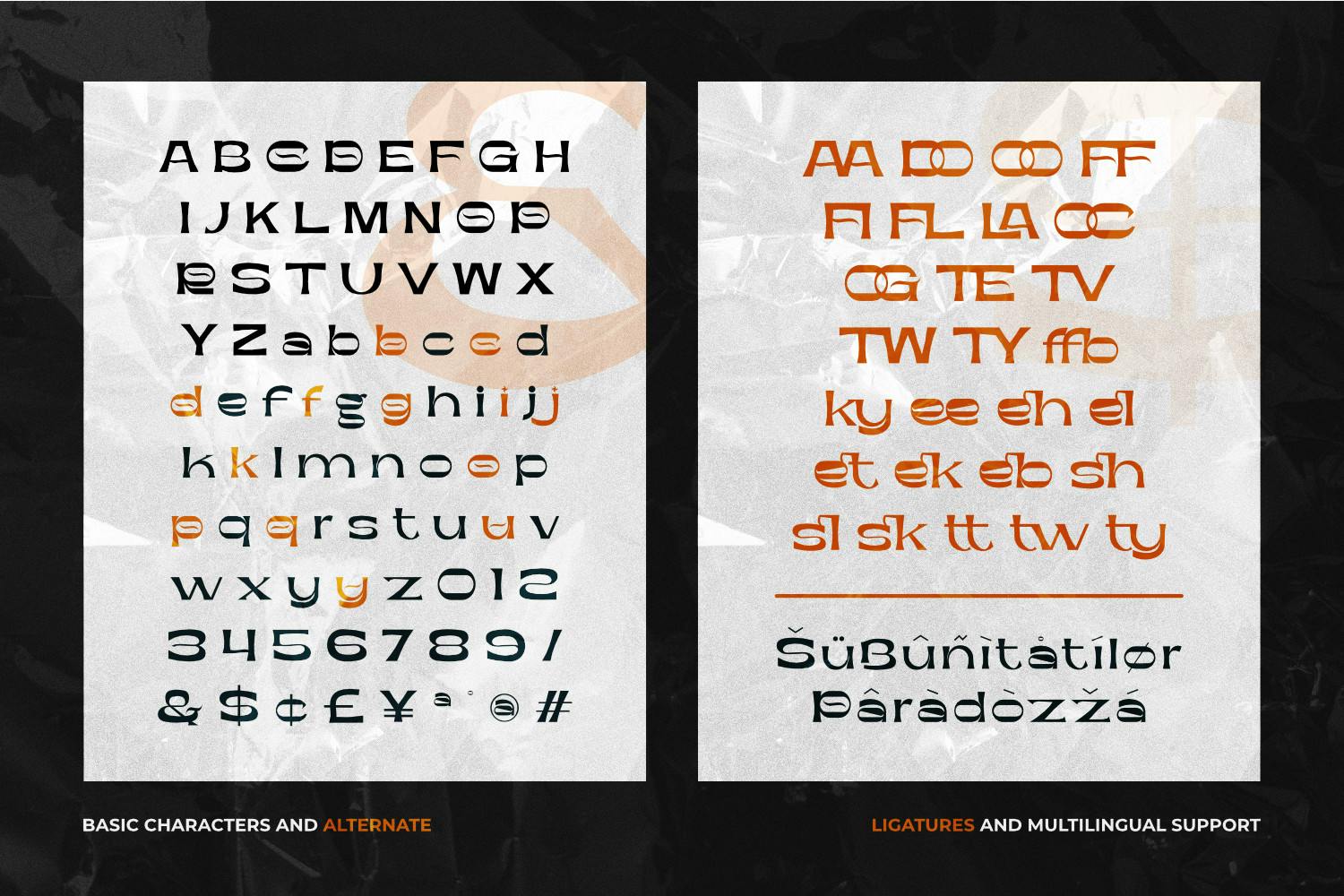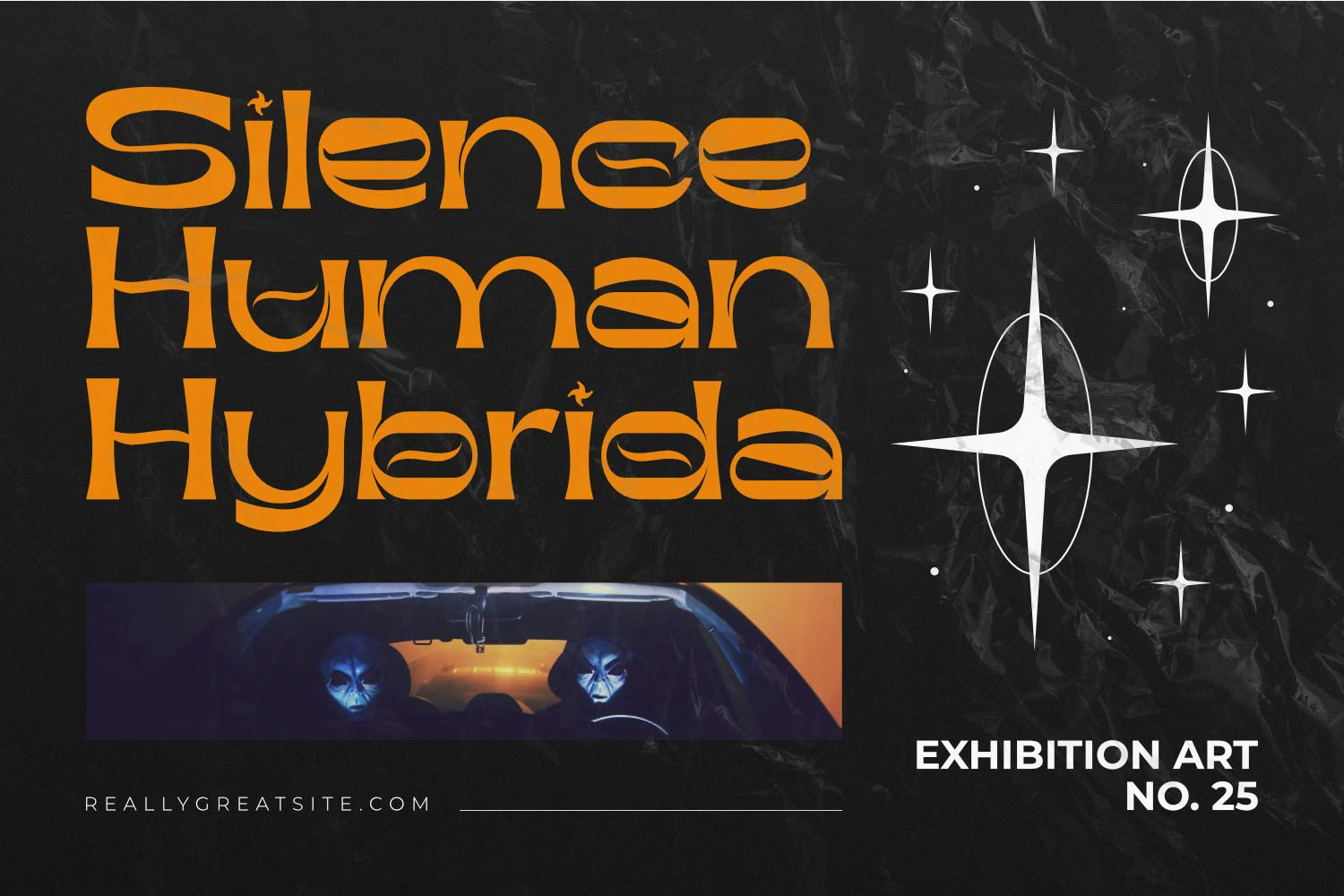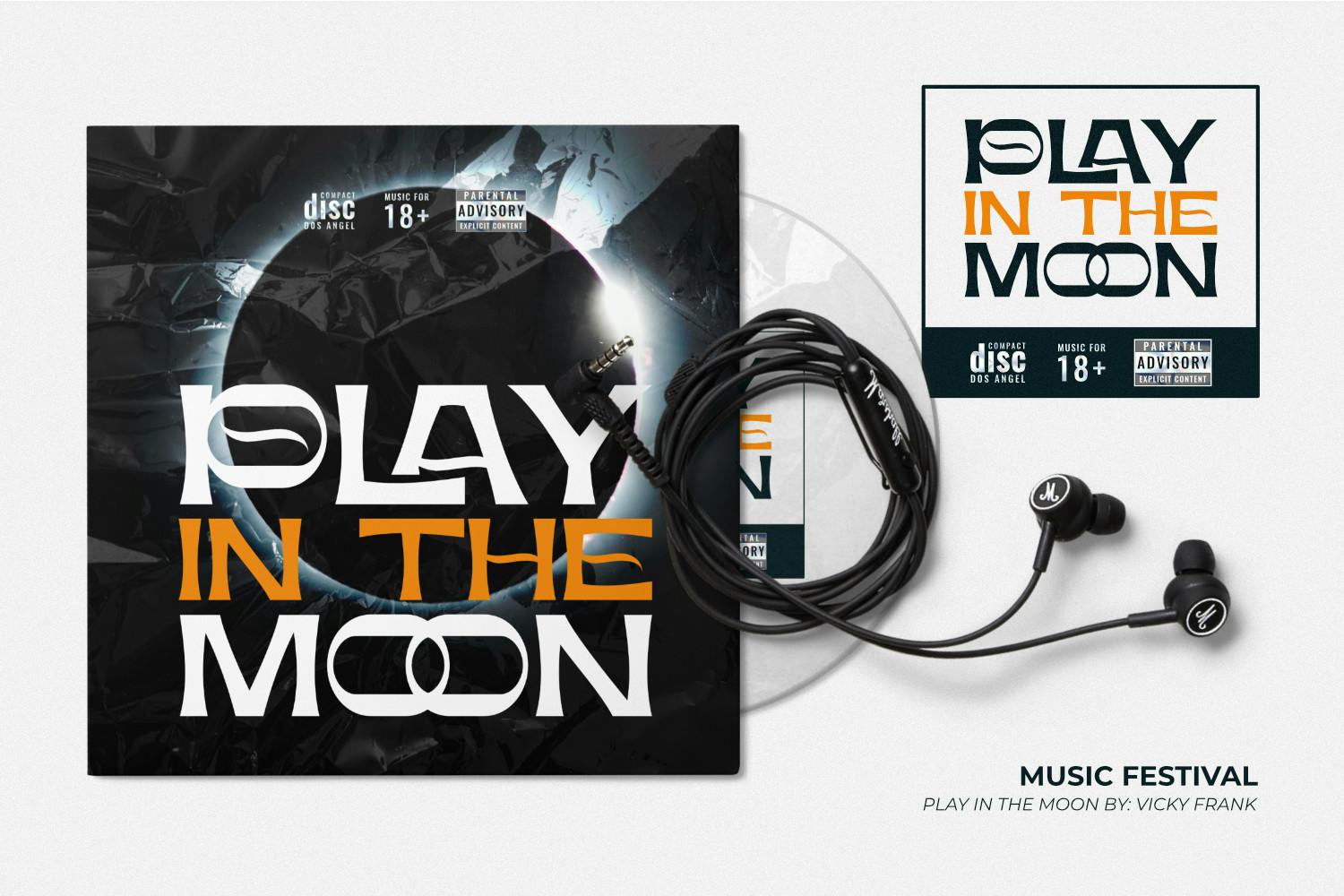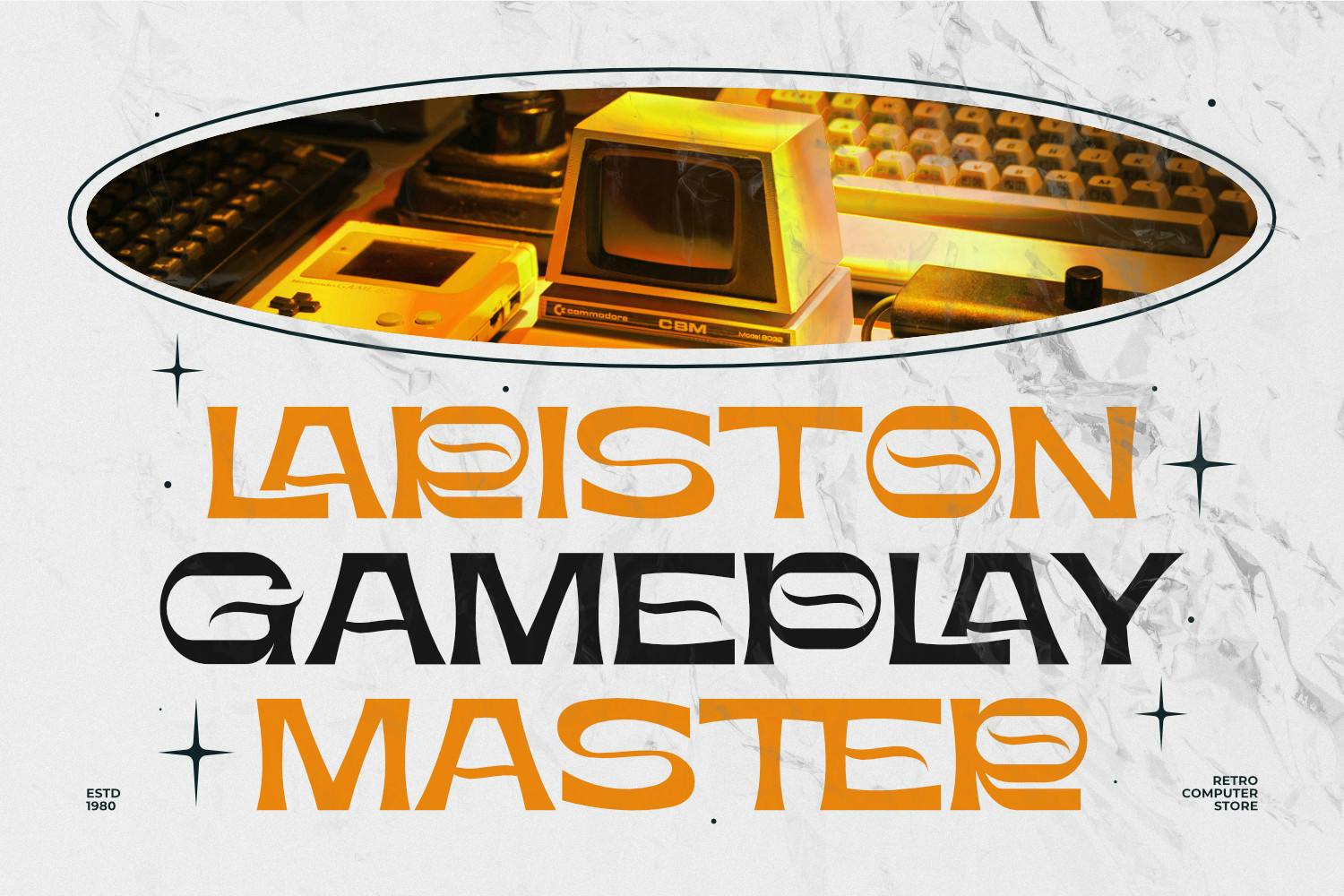
فونت مدرن Ragshie برای بسیاری از پروژههای شما مانند لوگو و برندینگ، عکاسی، دعوتنامهها، واترمارکها، تبلیغات، طراحی محصولات، لوازمالتحریر، طراحیهای عروسی، برچسبها، بستهبندی محصولات، رویدادهای ویژه و موارد بسیار دیگر مناسب است.